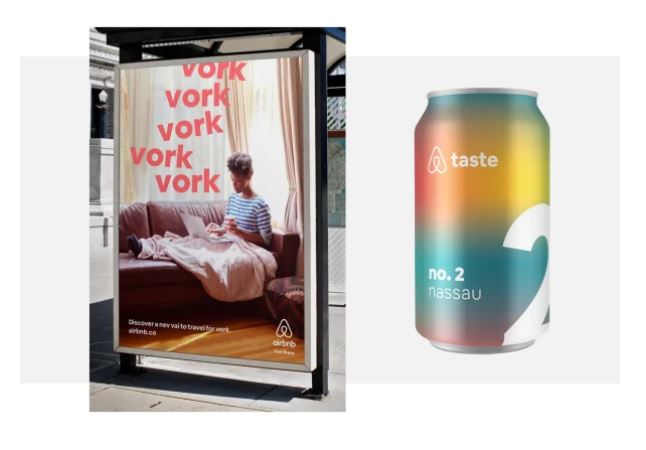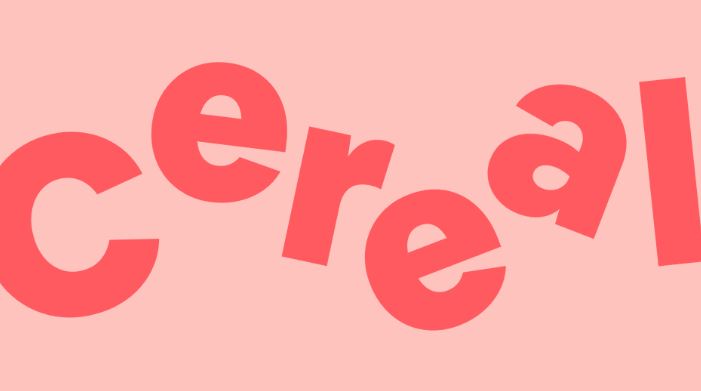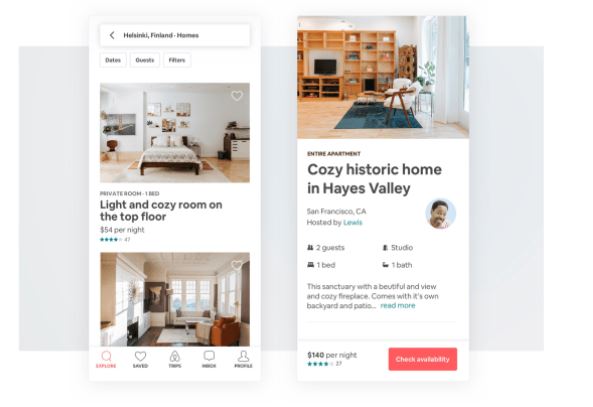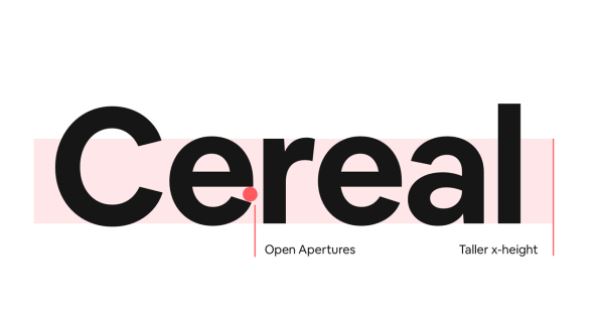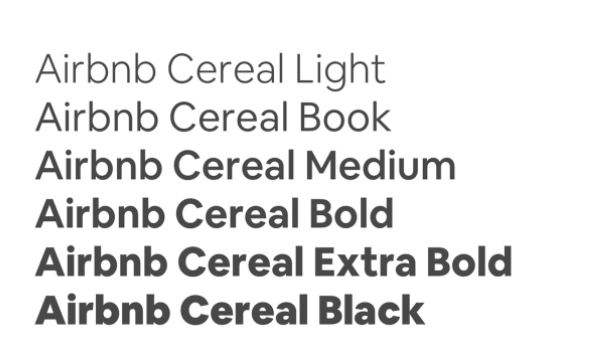
미래의 비밀 담은 에어비앤비 새 폰트 디자인, 시리얼
게시판에서 버튼에 이르기까지 모든 부분에 적용되는 에어비앤비의 커스텀 폰트인 ‘시리얼’을 통해 어떻게 이 브랜드가 마케팅을 개진하고 있는지 살펴보았다.
전통적 마케팅 방식에만 의존하지 않는 에어비앤비(Airbnb)는 제품 자체가 브랜드의 역할을 한다. 에어비앤비의 웹 사이트와 앱을 알리는 데에서는 슈퍼볼(Superbowl·30초짜리 중간 광고) 상업 광고의 중요성은 그다지 높지 않다. 오늘날 많은 앱과 웹 사이트의 모양새는 점점 엇비슷해지고 있다. 현대에 들어 웹을 돋보이게 하는 것이 바로 패턴 요소다. 에어비앤비의 브랜드가 제품의 역할을 하며, 그 제품은 마케팅의 방도 그 자체이다. 다시 말해, 제품 자체가 웹 디자인에 녹아들게 했고 현대적 감각으로 이 것을 풀어냈다.
새로운 시대에는 폰트가 큰 부담으로 작용한다. 이유인즉슨 폰트는 다양한 광고판에 맞춰 브랜드의 스토리를 담아야 하기 때문이다. 그 동시에 작디작은 UI 버튼에서 레이블로서 역할을 해야하기 때문이다. 에어비앤비는 2년 전 이러한 문제에 봉착해 유명 폰트 기업인 달튼막에 과제 해결을 위해 컨설팅을 의뢰했다. 그 결과 시리얼이 탄생했고 에어비앤비의 웹과 모든 프로그램에서 적용되고 있다. 현재 라틴 문자를 사용하는 12개 언어로 구성되어 있지만 향후 2년 이내에 러시아어에서 중국어까지 25개 패밀리 폰트로 확장해나갈 예정이다.
설령 일각에서는 폰트의 중요성에 대해 인지하지 못한다 하더라고, 에어비앤비 내부적으로는 시리얼 폰트 제작 사례가 조직의 광범위한 문제 해결과 조직 변화의 세부적인 필요조건들을 짚어주는 계기가 되었다. “타이포그래피 시스템은 어떤 디자인에도 가장 중요한 핵심이며 모든 터치 디자인의 접점에 있어 더욱 명확한 가이드를 제시하는 중요한 부분”이라며 “이것이 점점 더 많은 조직이 폰트에 대해 관심을 두는 이유라고 생각한다”라고 에어비앤비 디자인 팀장 알렉스 슈라이퍼는 말했다.
달튼막은 대개 디자인으로 표현하려고 하는 부분을 그려내기 전 일련의 워크숍을 진행한다. 달튼막의 크리에이티브 디렉터 톰 폴리(Tom Foley)는 “사람들 각각의 배경과 기대치가 다르기에 클라이언트와 진행하는 이와 같은 워크숍은 때로는 가장 어렵기도 한 부분으로 다가오기도 한다”고 밝혔다. 에어비앤비는 브랜드의 정체성에 대해 확신이 넘쳤으며 명확성과 확실함에 대한 강한 집념을 우리에게 별나도록 친근한 모습을 통해 보여주었다.
‘a’는 둥근 모양의 곡선과 만나는 지점의 특성이 있는 알파벳 문자다. 그래서 ‘a’를 디자인하기 위해 달튼막은 에어비앤비의 로고 “벨로”를 출발점으로 삼아 디자인 특성들을 파악했다. 벨로의 특이점은 캘리그라피와 같이 한 획으로 그릴 수 있다는 점이다. 달튼막의 대표 막은 “붓놀림과 같은 끝 지점을 집어넣는 줄기와 같은 세부 정보 덕에 한 획으로 그려진 것처럼 보이는 ‘a’를 만들 수 있었다”고 전했다. ‘a’를 기점으로 해 ‘B’와 ‘D’가 개발되었다.
폰트를 디자인함에 있어 가장 어려웠던 부분은 두 가지 용도를 가진 단일 종의 폰트 패밀리를 구성해야 한다는 점이었다. 이는 UI에 대한 밝은 폰트와 웨이트가 한층 무거운 볼트 폰트다. 슈라이퍼는 “광고판에서 버튼에 이르는 부분을 커버하기 위해 이와 같은 선택을 했으며 달특막 측에 이와 같은 요청을 했다”고 말했다. 이후 달튼막은 폰트 패밀리의 일부 웨이트(weight·폰트 두께의 가중치) 두 종을 디자인했고 이외의 웨이트의 폰트들은 익스트래펄레이션(Extrapolation·기존 개발된 웨이트의 폰트를 기반으로 하여 웨이트를 더해 다른 웨이트 형태를 찾아내는 자동화 디자인 시스템)으로 제작되었다.
그러나 폰트 디자인에서 소프트웨어가 할 수 있는 부분은 한계가 있다. 일반적으로 수많은 베리에이션(Variation·변형)을 걸치는 마스터 폰트와는 별개로 때에 따라 폰트 매쉬업(mashup·자연스럽지 않게 제작된 디자인)의 중간 웨이트 폰트가 폰트 디자인 소프트웨어를 통해 생성되기도 한다. “인터폴레이션(Interpolation·기존 개발된 웨이트의 폰트를 기반으로 하여 중간값의 웨이트 형태를 찾아내는 자동화 디자인 시스템)은 가장 낮은 웨이트와 큰 웨이트의 특성을 물려받는 것이다”라고 폴리가 말했다. 달튼막이 제시한 해결책은 중간의 골디락(Goldilock·과하지 않고 적절하다는 의미)의 특성을 지닌 제3의 마스터 폰트를 그리는 것이었다. 하여 좁은 영역과 굵은 영역 모두 적절한 균형을 유지하는 유동적인 알고리즘으로 더욱 다양한 웨이트를 탄생시켰다.
슈라이퍼는 시리얼 프로젝트와 브랜드 간 고려했던 부분들이 현대의 디자인 관습을 변화시켜야 하는 중요한 부분이자 촉매제가 되어야 한다고 주장하고 나섰다. 에어비앤비는 프로젝트에 브랜드 디자인과 제품(서비스) 디자인의 리드 역할을 따로 두지만 같은 프로젝트팀에 두고 하나의 전략으로 운용될 수 있도록 하고 있다. “제품 경험치가 하나가 되는 부분은 매우 중요하다고 여겨진다”고 슈라이퍼가 강조했다.
그가 강조했듯 20세기의 마케팅은 판매와의 개념을 다르게 보고 있다. 이렇듯 판매와 제품 개발은 다르다고 정의하고 있으며 50년간 광고 시장에 이러한 시각이 팽배했다. 슈라이퍼는 “우리의 웹 사이트는 가장 큰 마케팅 도구이며 오늘날 제품 개발과 판매의 경계가 존재해서는 안 된다”고 주장했다. 덧붙여 “우리가 인스타그램에 게시한 무언가가 제품의 경험치에서 보는 것과 큰 차이가 없다고 보며 팀을 구성하는 방법부터 창의적 회의를 진행하는 방법에 이르기까지 이를 위해 아낌없는 노력이 있어야 기업과 브랜드가 흥할 것”이라고 말했다.